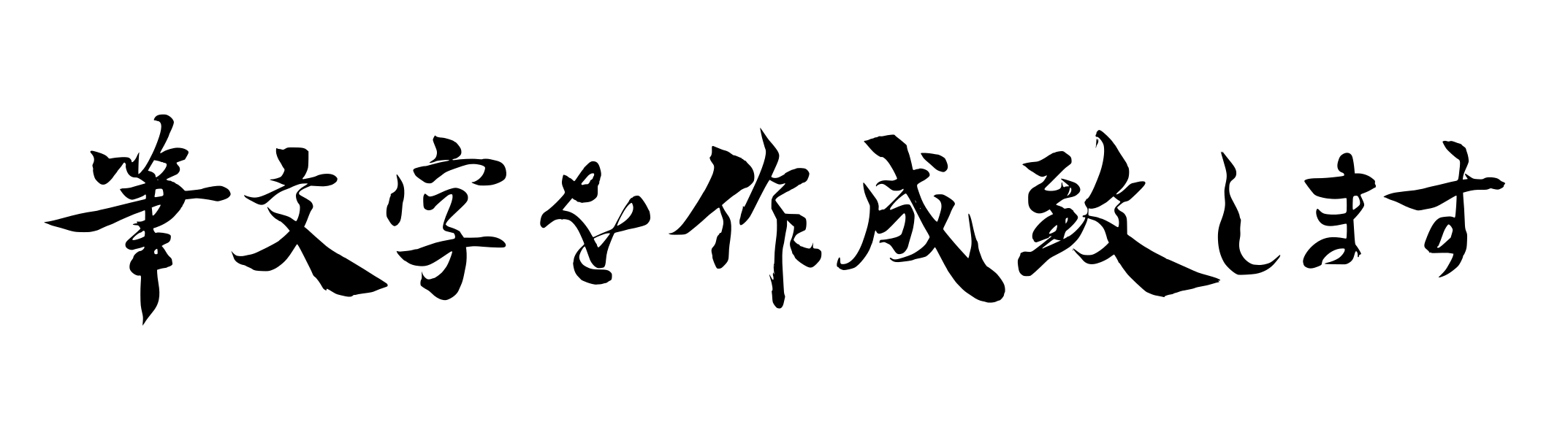
看板や商品名などの筆文字を、書家がオーダーメイドでご提供いたします。フォントではない完全オリジナルの筆文字の作成をご希望の際は是非当店へご依頼ください。
店の看板や商品パッケージに特別な筆文字を
あなたのお店や商品の魅力を、唯一無二の筆文字で表現しませんか?当サイトでは、経験豊富な書家が、店の看板や商品パッケージなどにふさわしい、心に響く筆文字を制作いたします。書家の技術と心が込められた筆文字は、商品やサービスの信頼性や効果を未来の顧客に伝え、心に深く残る印象を与える重要な役割を果たします。
どのような書体・雰囲気の筆文字でもお任せください。店名や社名、商品名、題名、標語など、ご指定の語句を、ご希望イメージに基づき、墨書いたします。筆文字フォントのように、どこかで誰かが同じ文字を使っている状態ではなく、完全にオリジナルなオーダーメイドの手書き筆文字です。店舗や商品などの個性を際立たせ、魅力を向上させるハイクオリティーな筆文字をご提供いたします。
サービスの特徴
・完全オーダーメイド
お客様のご要望に応じて、一つ一つ丁寧に手書きで制作します。
・複数案の提示
5~8案ほどご提案し、お客様に最適なものを選んでいただけます。
用途
あらゆる用途の筆文字を制作いたしております。
用途の一例
・居酒屋や鮨店、焼肉店、日本料理店など、飲食店看板
・食品パッケージ、商品パッケージ
・焼酎ラベル、日本酒ラベル
・会社名、屋号、ブランド名、アーティスト名、団体名
・スーパー銭湯の名称、サウナ施設名、銭湯名など、温浴施設看板
・温泉旅館名
・映画、漫画、アニメのタイトル
・舞台公演の題字
・イベント名
・横断幕や懸垂幕の標語、チームスローガンなどの熟語
・墓石、墓碑に彫る「愛」などの言葉
・玄関表札、名刺
・DVDジャケットの作品タイトル
・CDジャケットの楽曲タイトル
・書籍のタイトル
・広告・パンフレット・ポスター・CM
・暖簾(のれん)、のぼり旗
・企業理念・社是・社訓
看板や商品名の筆文字の魅力と、書き手選びの重要性
看板や商品パッケージのデザインは、消費者の購買行動に大きな影響を与える要素の一つです。手書きの筆文字を用いた看板やパッケージデザインは多種多様なジャンルで見られ、フォントでは再現できない独特の温もりや美しさ、生命感が消費者の心を惹きつけます。
例えば、味噌や豆腐、うどん、漬物、日本酒、焼酎、お茶などの伝統的な食品や飲料のパッケージに筆文字を採用することで、その歴史や精神性、こだわりを感じさせることができます。
看板や商品パッケージの筆文字は、単に店名や商品名を伝えるだけではなく、ブランドイメージやコンセプト、品質や特徴を伝達する象徴的な役割も担っているのです。
しかし、筆文字は存在感が強く、商品名への印象が増幅されますので、良くない筆文字を使うと粗悪なイメージにつながります。せっかく中身が素晴らしくても、それを消費者に想起させられません。良い筆文字であればこそ、店や商品の価値を高める効果があります。筆文字を用いる際には、商品価値や店舗イメージを損なわないために、看板や商品パッケージ専門の書家に依頼することをおすすめします。
看板や商品パッケージへ手書きの筆文字を用いることは、日本の伝統美を用いて効果的に消費者へアピールできる素晴らしい手法です。その効果を最大限に活かすため、書き手選びに是非こだわってみてください。